Me declaro un enamorado de la tipografía. Del antidogma limpio de Weingart al comercialismo espléndido de Lubalin, de la pulcritud excelsa de Adrian Frutiger a la rebeldía incomprendida de Carson… y aunque definitivamente me declaro más atraído hacia la función que a la forma, creo que cualquier buen experimento tipográfico es inspirador y seductor.
Por estas razones me permito compartir con ustedes estos tres ejercicios; los dos primeros, ganadores en los Summit International Awards, mientras que el tercero es un efectivo diseño para publicitar la National Trasplant Society. El trío de piezas me parecieron un portento, no sólo por su excelente manejo tipográfico sino por su espléndida reticencia.
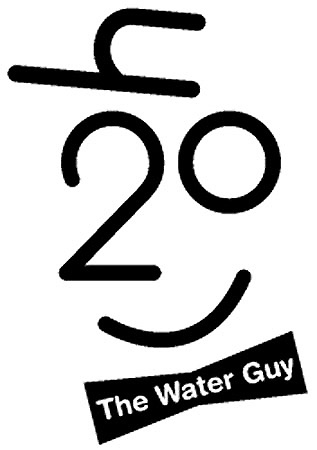
El primero utiliza la fórmula del vital líquido, H2O, para detallar el rostro de “el hombre del agua”, un tema álgido de conciencia social en nuestro tiempo.
El segundo se constituye como un interesante juego que lanza una pregunta al espectador: ¿Ves doble? Si la respuesta es sí, problema y solución ocurren simultáneos, pues estás borracho, pero de forma mágica, te encuentras ante la respuesta: AA. Sencillísmo pero contundente.
Finalmente, el tercero maneja los caracteres cual si fueran piezas intercambiables, una idea encantadora si tomamos en cuenta que el tema es donación de órganos. Brillante.
Llama la atención que los tres diseños estén enfocados al marketing social… ¿será que la inicativa privada es más temerosa siempre de la experimentación?